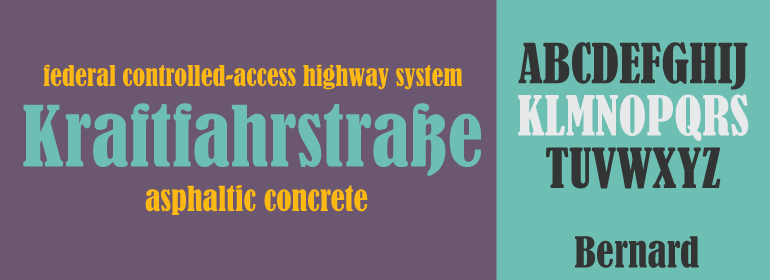
Monotype Bernard™
Monotype Bernard™,这款字体结构工整、笔画清晰,兼顾美观与易读性,适用于标题、正文、海报、包装、LOGO 等多种场景。字形优雅稳定,风格百搭耐看,适配日常排版与创意设计,让文字呈现更舒适、更具质感。Monotype Bernard™一笔一画,皆是细节,以均衡的比例、流畅的线条打造舒适视觉体验,字形端正大气,风格简约现代。无论是商业设计、品牌宣传还是日常排版,都能轻松驾驭,让文字更有格调与力量。Monotype Bernard™字体下载。
在二十世纪初,大量柔和的又有点手写风格的Roman字体逐渐得到发展。尽管就第一次世界大战后出现的主要设计影响而言,它们并不代表未来,但它们与过去截然不同,并在19世纪二三十年代得到了进一步发展。Monotype Bernard Condensed与这段时期密切相关,一种细窄的罗马风格唤起一种从容的魅力。Monotype Bernard Condensed字体适用于那些需要热情友好的显示应用。
In the early years of the twentieth century a number of romans with a soft and slightly script like quality were evolved. Although they did not represent the future in terms of the major design influences that were to appear after the First World War, they were a break with the past, and were developed further in the nineteen twenties and thirties. Monotype Bernard Condensed is closely associated with this period, a condensed roman evoking an easy charm. The Monotype Bernard Condensed font offers many display applications where warmth and friendliness is required.